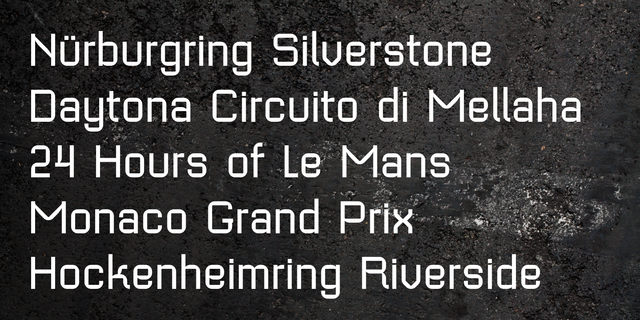
Шрифт Геомантикус – геометрический модульный гротеск с техногенным характером. Разработан в студии 2D Typo Лукьяном Турецким в 2012 году.
Ассоциации c семейством GeomanticusКачества и характер:
космический, лаконичный, твердый, статичный, точный, ровный, устойчивый, автоматический, искусственный, холодный, машинный, инженерный, прямой, индустриальный, современный, техногенный, прямоугольный, футуристичный, компьютерный, электронный, урбанистический, безразличный, равнодушный, чертежный, железный, стальной, надежный, уверенный, сильный, кинематографичный
техника, прибор, фантастика, конструктор, чертеж, инженер, автоматика, робот, электроника, компьютер, космос, наука, проводка, инновации, гаджет, девайс, урбанистика, игра, Айтишник, IT, айтишник, айти, технологии, андроид, железо, инструмент, ракета, спутник, ремонт, кино, киберспорт, компьютерная игра Стилистика: